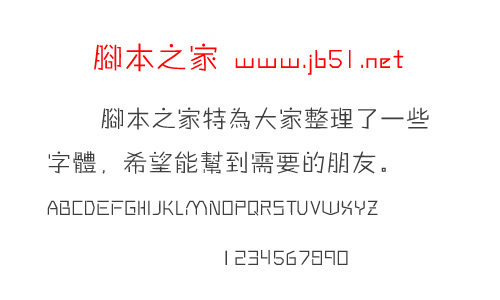
方正稚藝繁體字體是方正字體庫中的一種字體,方正稚藝是一款富有孩童氣息的創(chuàng)意字體。這款字體的筆形主要是由圓點和直線構(gòu)成,重心偏低,有兒童書寫的簡拙;筆畫交接處多有書寫意味的分離,筆畫中圓形的點畫與其他直線筆畫形成對比,靈動可愛。字形輪廓整體統(tǒng)一,具有一定的易讀性。方正稚藝的個性乖巧靈活,清新萌動。不但適用于兒童類的書刊、品牌廣告和產(chǎn)品包裝設計,以及社交網(wǎng)絡的個性化用字,還可勝任簡短的正文排版。喜歡的朋友們可以前來下載使用。